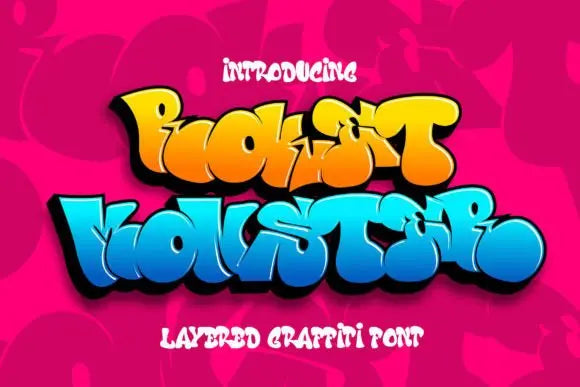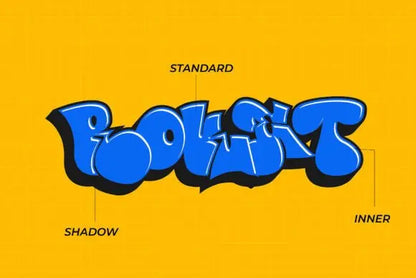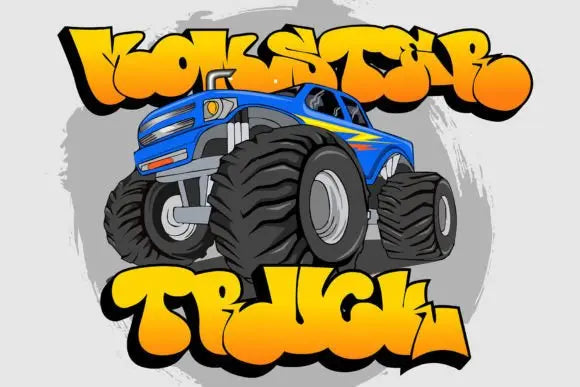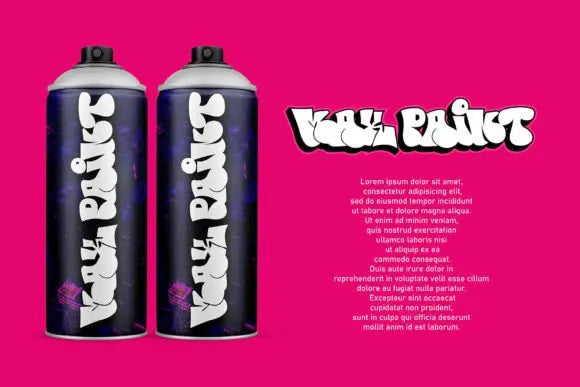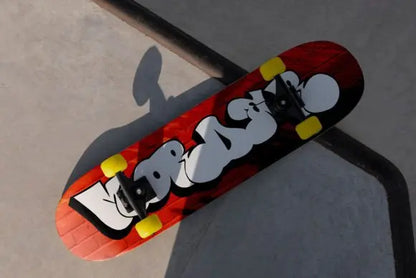
Fuente Rocket Monster
Roket Monster es una fuente de graffiti urbano caracterizada por bordes afilados y una apariencia atrevida. Ideal para carteles musicales, diseños de indumentaria, camisetas y ropa urbana, esta fuente aporta un toque vanguardista a tus proyectos. El estilo único de “Roket Monster” lo convierte en la elección perfecta para temas de estilo callejero o graffiti urbano.
Ya sea que desee crear una declaración fuerte y poderosa o simplemente agregar un toque de actitud a sus diseños, "Roket Monster" es la fuente para usted.